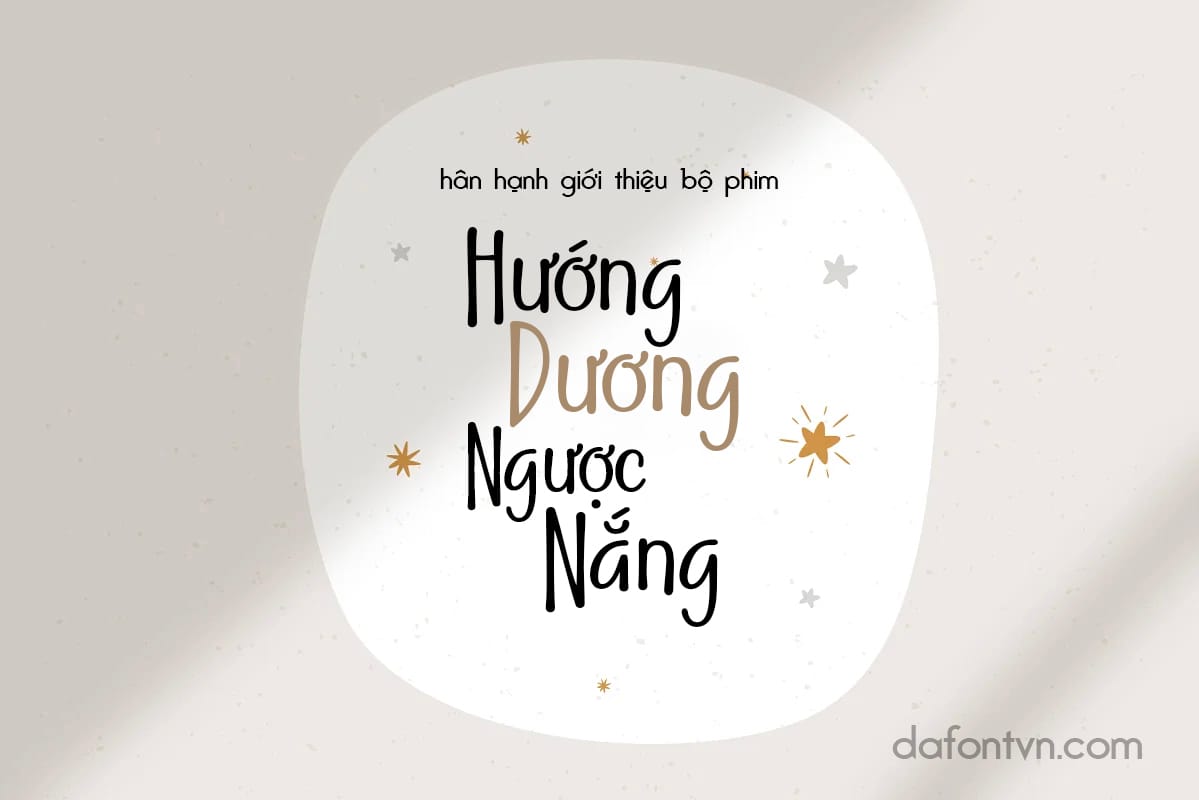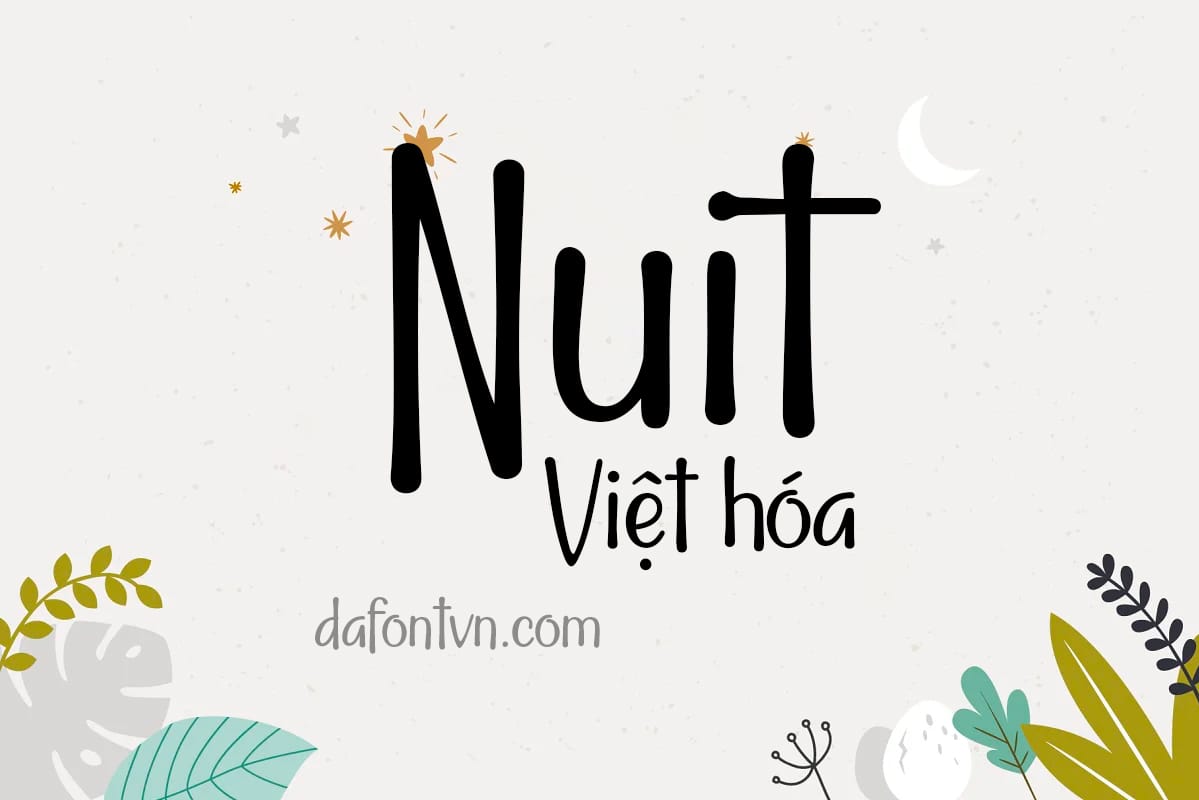
Nuit, một font chữ được viết tay thú vị với tính cách mạnh mẽ được thiết kế bởi Carine de Wandeleer. Với các thiết kế ấn tượng của font sẽ mang lại cho bạn những thiết kế ấn tượng. Độ đậm và độ mỏng trong các nét vẽ của chúng tạo nên một sự hài hòa ấn tượng.